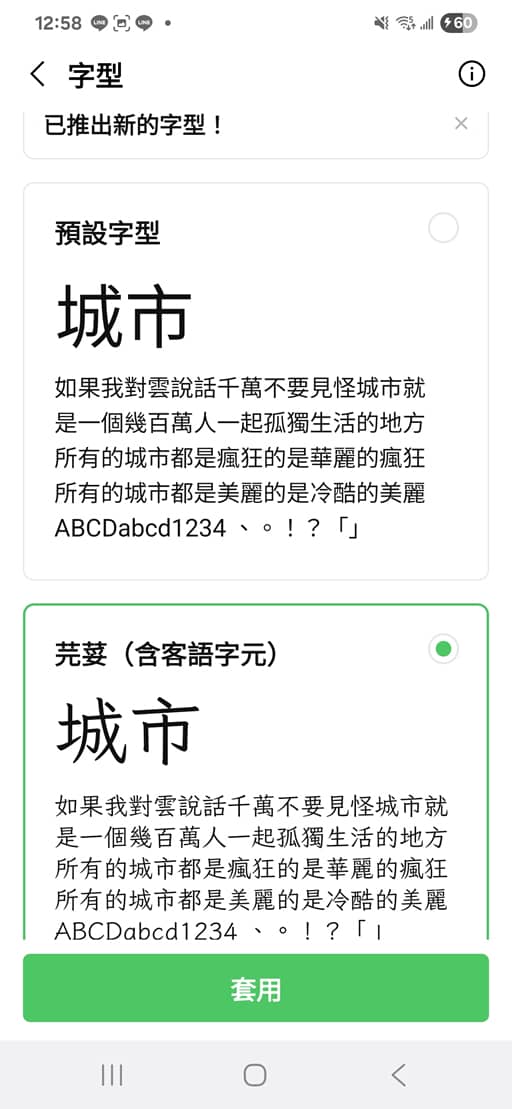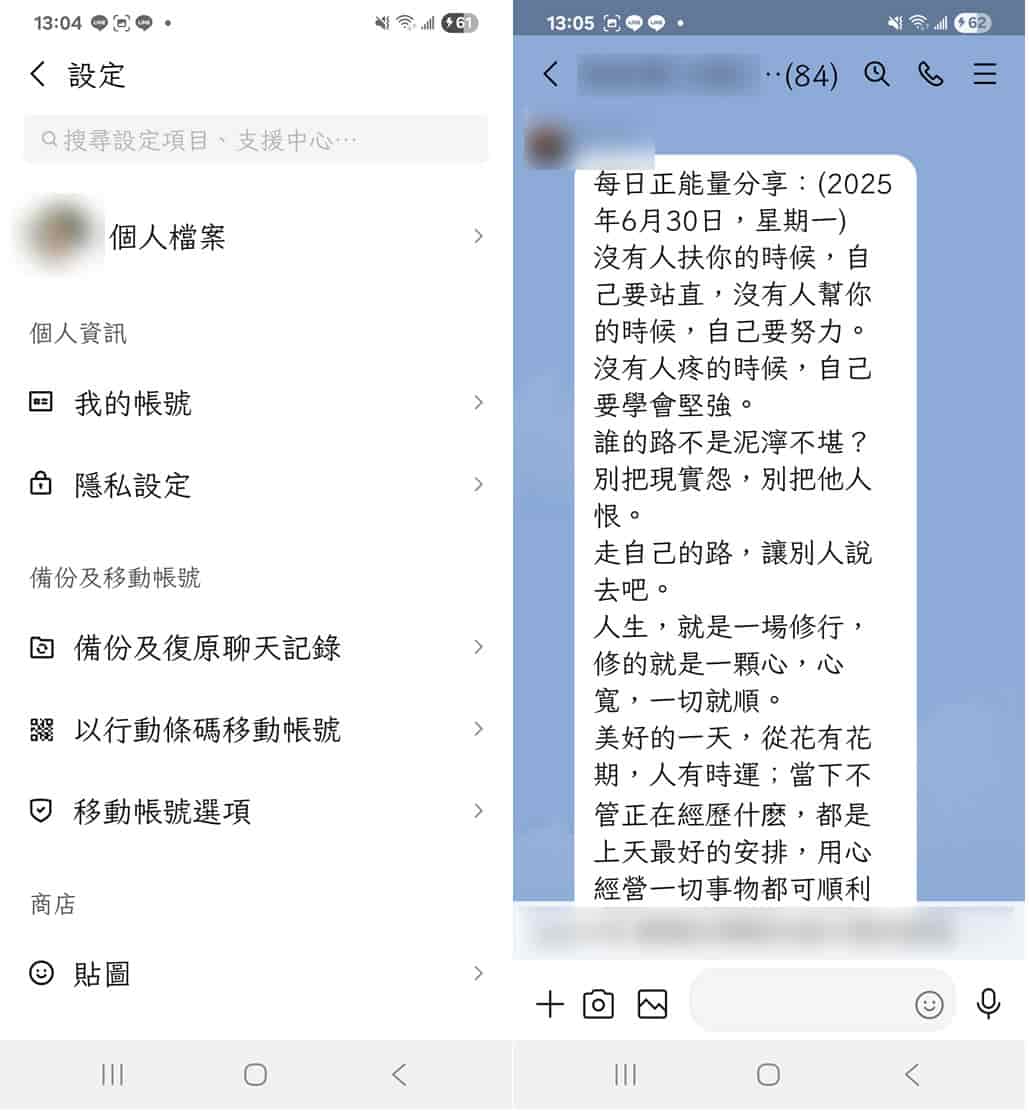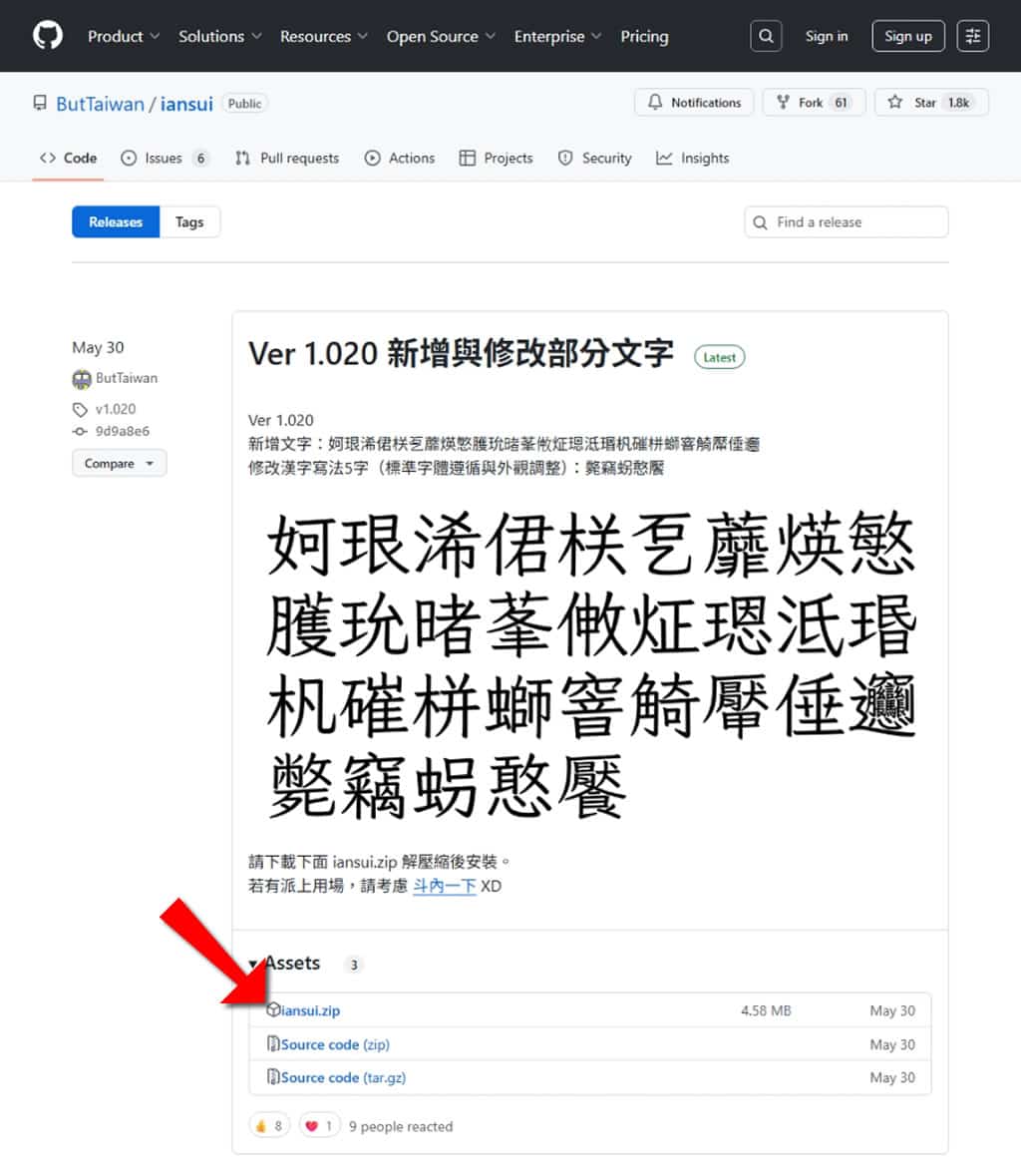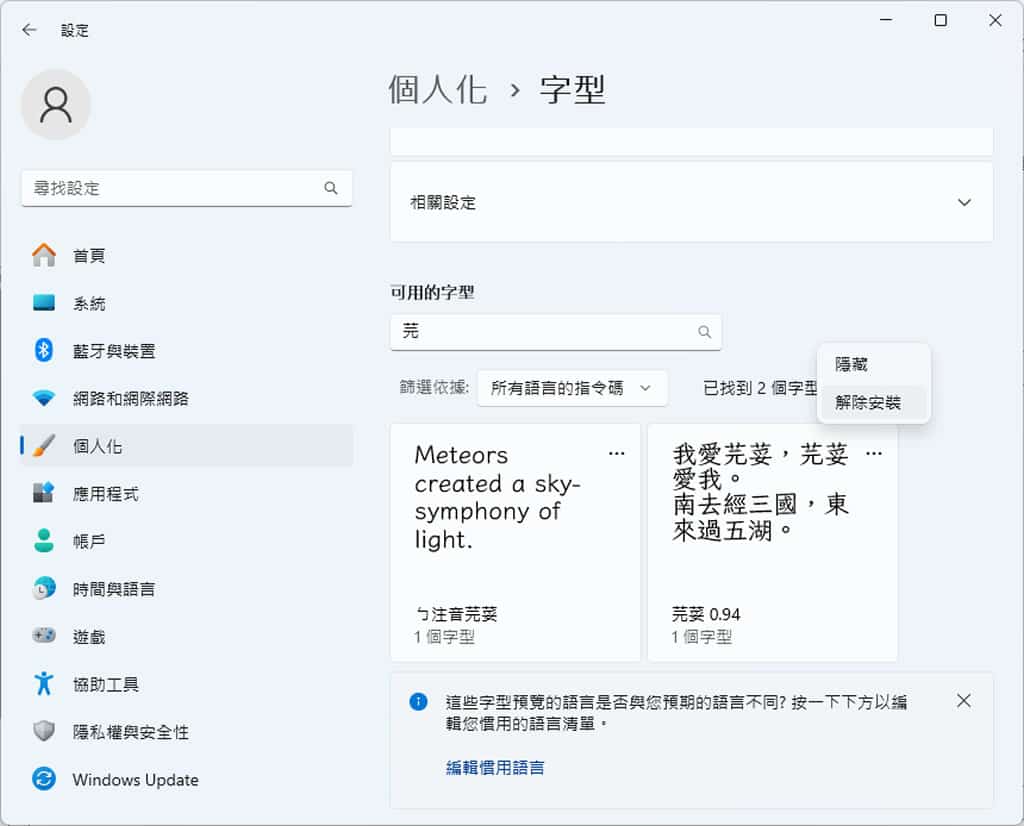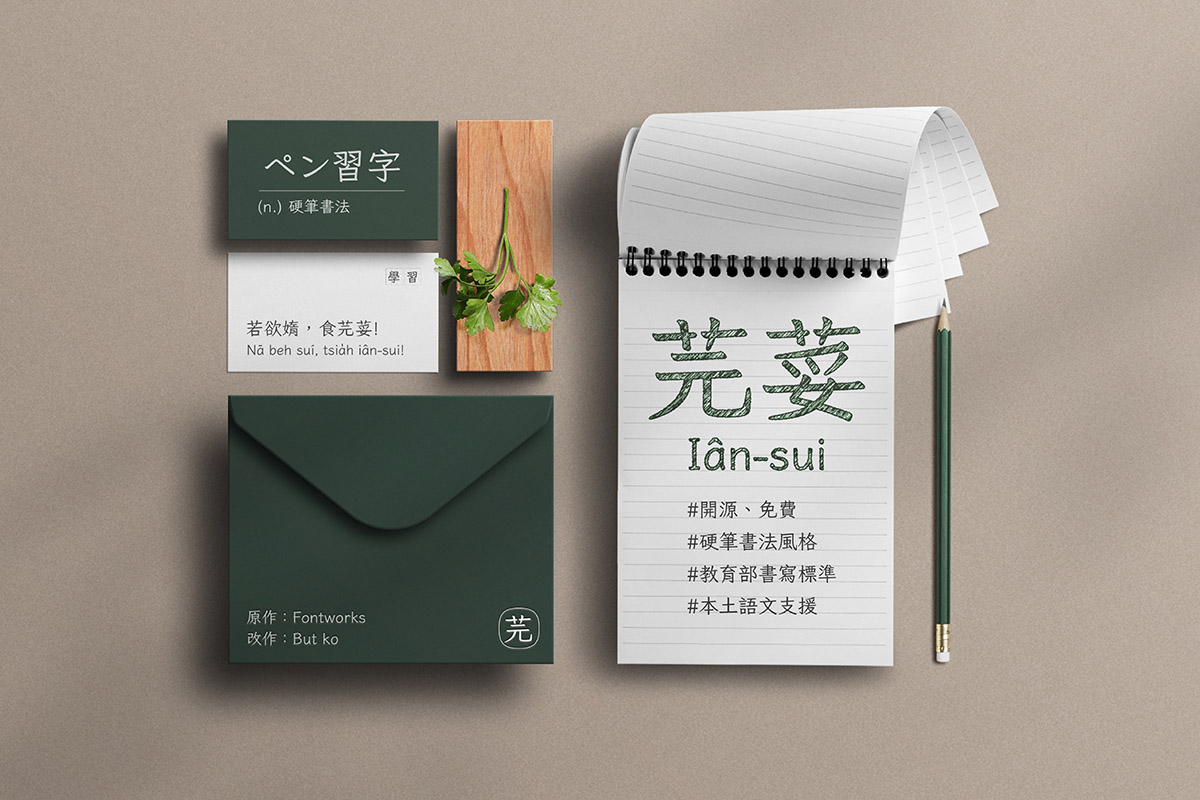
LINE 官方於 2025 年 2 月正式推出全新免費字型「芫荽」(音同「元雖」),這款字型不僅僅是單純的視覺美化工具,更是一座重要的文化橋樑。芫荽字型基於日本開源字體 Klee One 進行改良,專門補充了台灣本土語言用字,包括客語漢字、台語漢字、原住民族語羅馬字等特殊字符,讓使用者在數位溝通時能夠更精準地表達本土語言內容。這款字型採用手寫風格設計,筆畫力道清晰有力,呈現出如同鉛筆書寫的自然質感,不僅提升了 LINE 介面的視覺層次,更重要的是為台灣繁體中文使用者帶來更完整的數位語言體驗。
「芫荽」字型收錄字數
- Big5範圍內約8,170字。注意並沒有包含Big5完整的13,560字。
- 支援jf當務字集0.9基本包與擴充包所有文字。
- 台、客語漢字(教育部《臺灣台語常用詞辭典》《臺灣客家語常用詞辭典》內所有推薦用字。原則上不收錄異用字。)、常用粵語字。
- 注音符號與方音符號。
- 支援台羅拼音、台語白話字拼音、客語拼音、客語白話字拼音、原住名族語拼音、漢語拼音、馬祖福州話拼音編排。
- 依繁體中文習慣,全形標點符號置中。括弧引號類亦調整為稍比日文原形向中靠攏。
- 數字 7、英文大寫字母 I 亦調整為更貼近台灣教科書的寫法。
支援 KK 音標、DJ 音標所需之所有字母與重音符號,可從下表複製使用:
- KK: ɑ æ ɛ ə ɪ ɔ ᴜ ʌ ɚ ɝ aɪ aᴜ θ ʃ ð ʒ ŋ ḷ ṃ ṇ ‵ ʹ ͵
- DJ: ɑ æ ə ɜ ɪ ɔ ʊ ʌ ː aɪ aʊ θ ʃ ð ʒ ŋ ˈ ˌ
- 注意:芫荽字型的 a 預設為單層,遇到 ɪ、ᴜ、ʊ 等字母會自動呈現為雙層 a,無需特意輸入 ɑ。